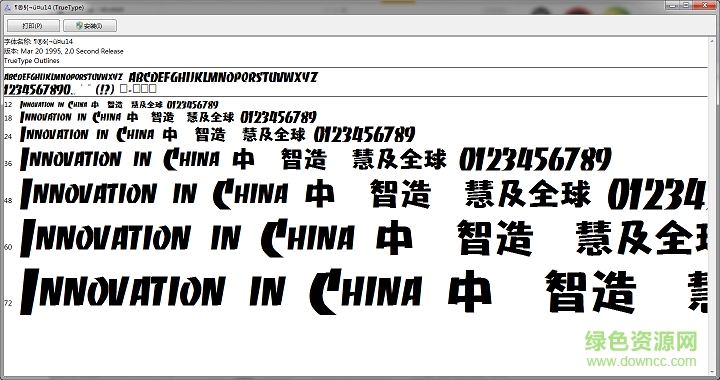
雅坊美工14字體是一款粗黑的中文字體。該字體略帶圓弧角,有點(diǎn)每個(gè)字有點(diǎn)像中擠攏的感覺(jué),不少綜藝節(jié)目都用過(guò)這款字體。喜歡的朋友,趕快下載體驗(yàn)吧!
1.雅坊美工字體俏皮可愛(ài)的字體,是常用于影樓攝影中的藝術(shù)字體
2.也適用于名片設(shè)計(jì)、平面設(shè)計(jì)、廣告設(shè)計(jì)、報(bào)紙雜志、企業(yè)LOGO、商標(biāo)注冊(cè)、電視臺(tái)廣告等領(lǐng)域。
3.其字形夸浮夸張揚(yáng),好似個(gè)調(diào)皮的孩子,活潑靈動(dòng),古靈精怪。